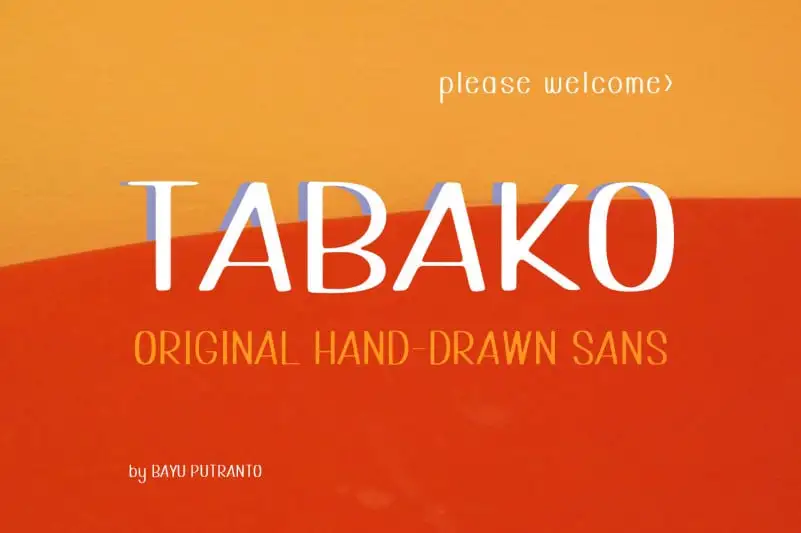
A Tabako Free Font é uma sans-serif bold e desenhada à mão, com a característica rústica e vintage do estilo urbano. Perfeita para logotipos, selos, tipografia e qualquer design vintage que você possa imaginar. Inspirada no trabalho de Bayu Putranto, essa família de fontes foi projetada para um look moderno e atemporal. Ela é ideal para marcas de marca, revistas, outdoors, logotipos, títulos, blogs e muito mais. A fonte vem com uma gama completa de letras maiúsculas e minúsculas, números, pontuação e suporte multilíngue. A Tabako Free Font é perfeita para quem busca um toque único e vintage em seu design. Hamilton é o designer responsável por essa fonte dinâmica e versátil, que traz à tona a essência urbana num moderno formato. Sem dúvida, esta é uma opção fantástica para aqueles que querem adicionar profundidade e personalidade ao seu projeto visual sem sacrificar a legibilidade ou estilo único.